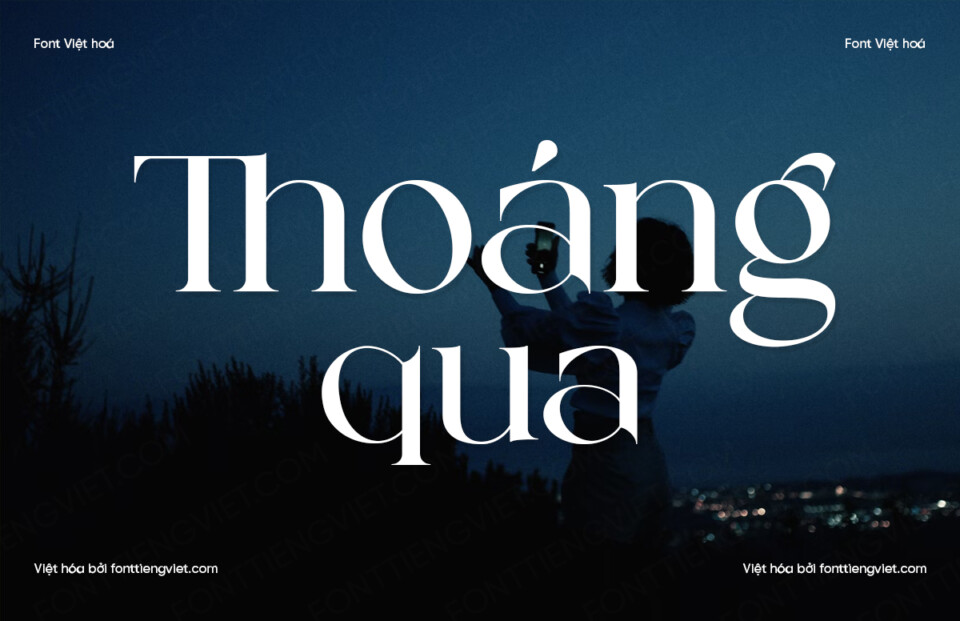
Font Việt hóa 1FTV VIP Chetta Vissto
Giới thiệu về bộ Font Việt hóa 1FTV VIP Chetta Vissto.jpg
Trong thế giới thiết kế đồ họa hiện đại việc lựa chọn một bộ Font Miễn Phí có hỗ trợ tiếng Việt đầy đủ là yếu tố then chốt để tạo nên sự chuyên nghiệp. Font Việt hóa 1FTV VIP Chetta Vissto.jpg nổi lên như một lựa chọn hàng đầu cho những ai yêu thích phong cách tối giản nhưng không kém phần tinh tế. Đây là bộ phông chữ được tinh chỉnh kỹ lưỡng về dấu câu giúp các nhà thiết kế tại Việt Nam dễ dàng áp dụng vào nhiều dự án khác nhau từ in ấn đến truyền thông kỹ thuật số. Sự xuất hiện của 1FTV VIP Chetta Vissto mang lại làn gió mới cho cộng đồng sáng tạo với những đường nét thanh mảnh và hiện đại.
Đặc điểm nổi bật của Font Việt hóa 1FTV VIP Chetta Vissto.jpg
Bộ phông chữ này sở hữu cấu trúc hình học cân đối tạo cảm giác dễ nhìn và thân thiện với người dùng. Khi sử dụng Font Việt hóa 1FTV VIP Chetta Vissto.jpg bạn sẽ nhận thấy sự tỉ mỉ trong từng nét vẽ đặc biệt là các ký tự có dấu vốn thường gặp lỗi trong các bộ font gốc nước ngoài. Với phiên bản VIP này mọi vấn đề về khoảng cách chữ và độ dày nét đều được tối ưu hóa để đảm bảo hiển thị sắc nét trên cả màn hình điện thoại lẫn các bản in khổ lớn. Điều này giúp nâng cao trải nghiệm đọc và tạo ấn tượng mạnh mẽ với người xem ngay từ cái nhìn đầu tiên.
Ứng dụng thực tế của Font Việt hóa 1FTV VIP Chetta Vissto.jpg
Nhờ vào tính linh hoạt cao Font Việt hóa 1FTV VIP Chetta Vissto.jpg được ứng dụng rộng rãi trong nhiều lĩnh vực khác nhau. Đối với các bạn học sinh và sinh viên bộ font này là công cụ đắc lực để thiết kế slide thuyết trình bài tập lớn hoặc làm báo tường kỹ thuật số. Trong khi đó đối với các doanh nghiệp đây là lựa chọn tuyệt vời cho thiết kế logo bộ nhận diện thương hiệu hay các ấn phẩm quảng cáo trên mạng xã hội. Sự thanh lịch của Chetta Vissto giúp thông điệp của bạn trở nên sang trọng và đáng tin cậy hơn trong mắt khách hàng tiềm năng.
Việc sử dụng các bản Việt hóa từ những nguồn uy tín như 1FTV giúp bạn tiết kiệm thời gian chỉnh sửa lỗi font một cách đáng kể. Font Việt hóa 1FTV VIP Chetta Vissto.jpg không chỉ đẹp về mặt thẩm mỹ mà còn đảm bảo tính kỹ thuật cao. Các ký tự đặc biệt trong tiếng Việt như “đ”, “ơ”, “ư” được thiết kế đồng nhất với phong cách chung của bộ chữ tránh tình trạng lệch tông thường thấy ở các font tự chế. Ngoài ra việc cung cấp dưới dạng file ảnh JPG mô phỏng giúp người dùng dễ dàng hình dung kết quả cuối cùng trước khi quyết định cài đặt vào hệ thống máy tính của mình.
Kết luận về giá trị của bộ font VIP